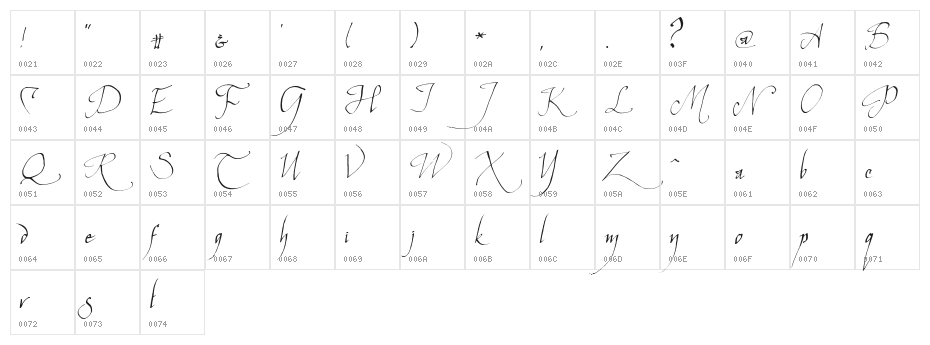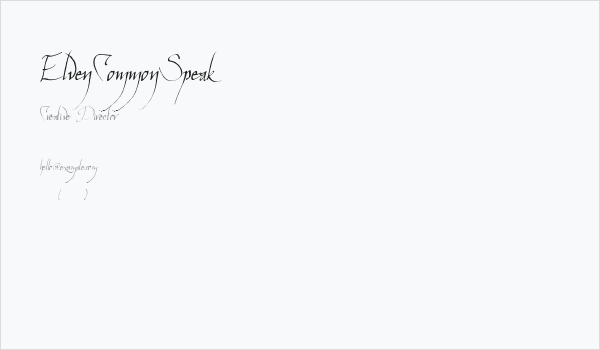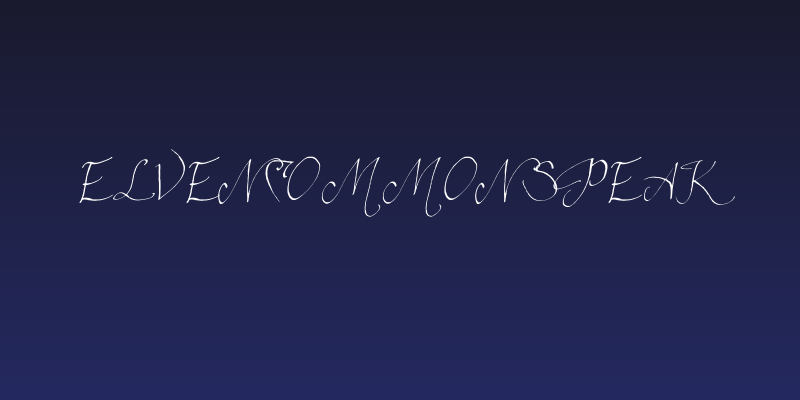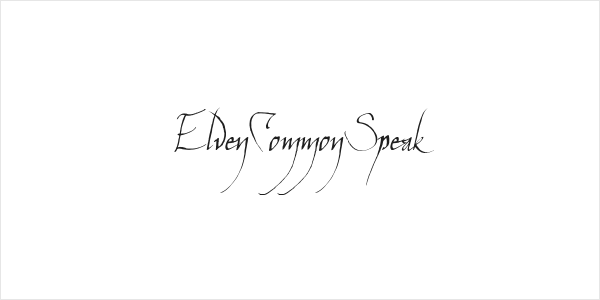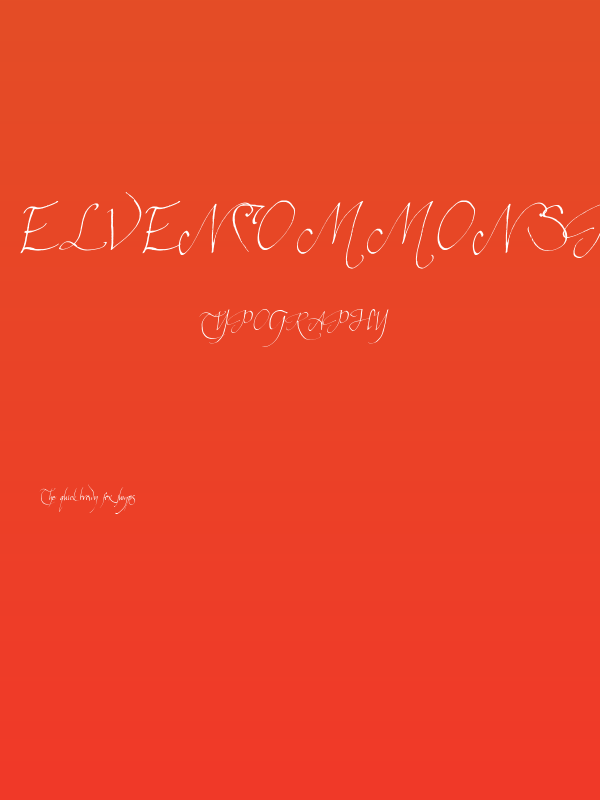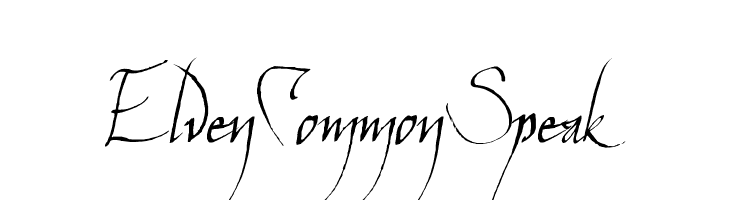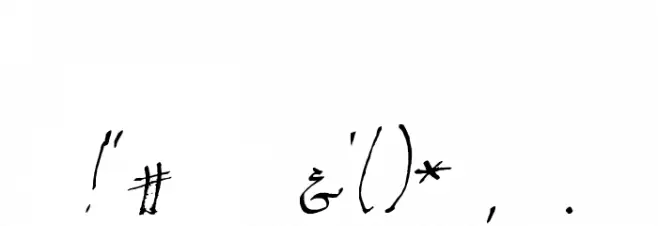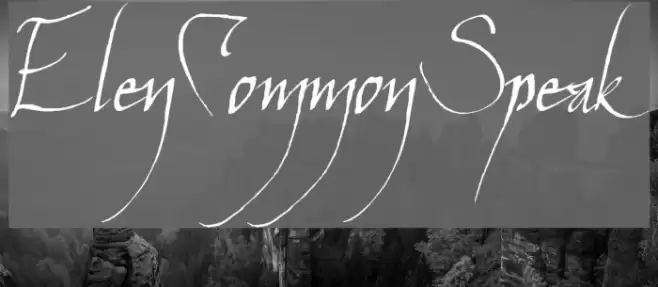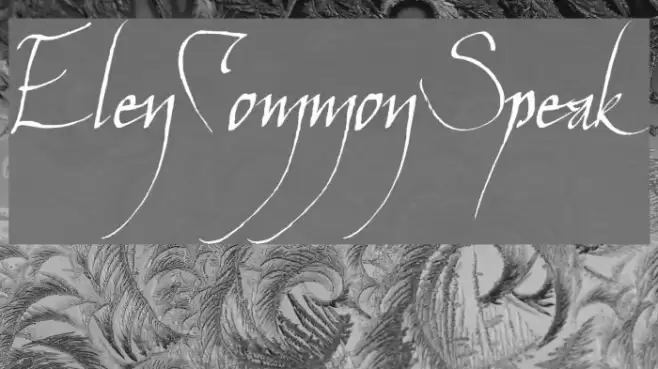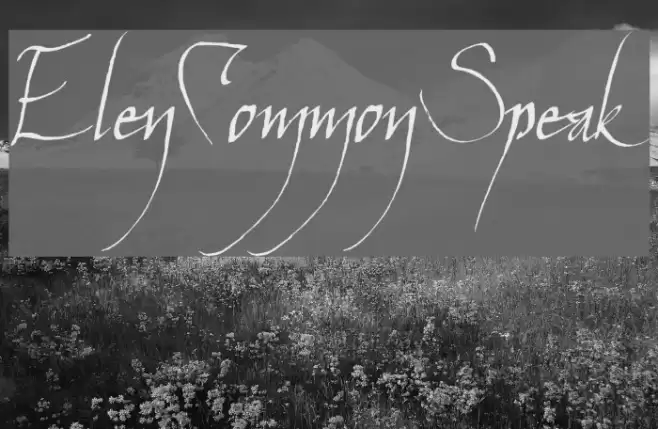
ElvenCommonSpeak Font
| समग्र शैली | Decorative |
| उपयोग का मामला | Logos, Invitations, Book covers |
| सुझाए गए प्रोजेक्ट | Ideal for fantasy-themed projects, book covers, invitations, or any design requiring an elegant, otherworldly touch. |